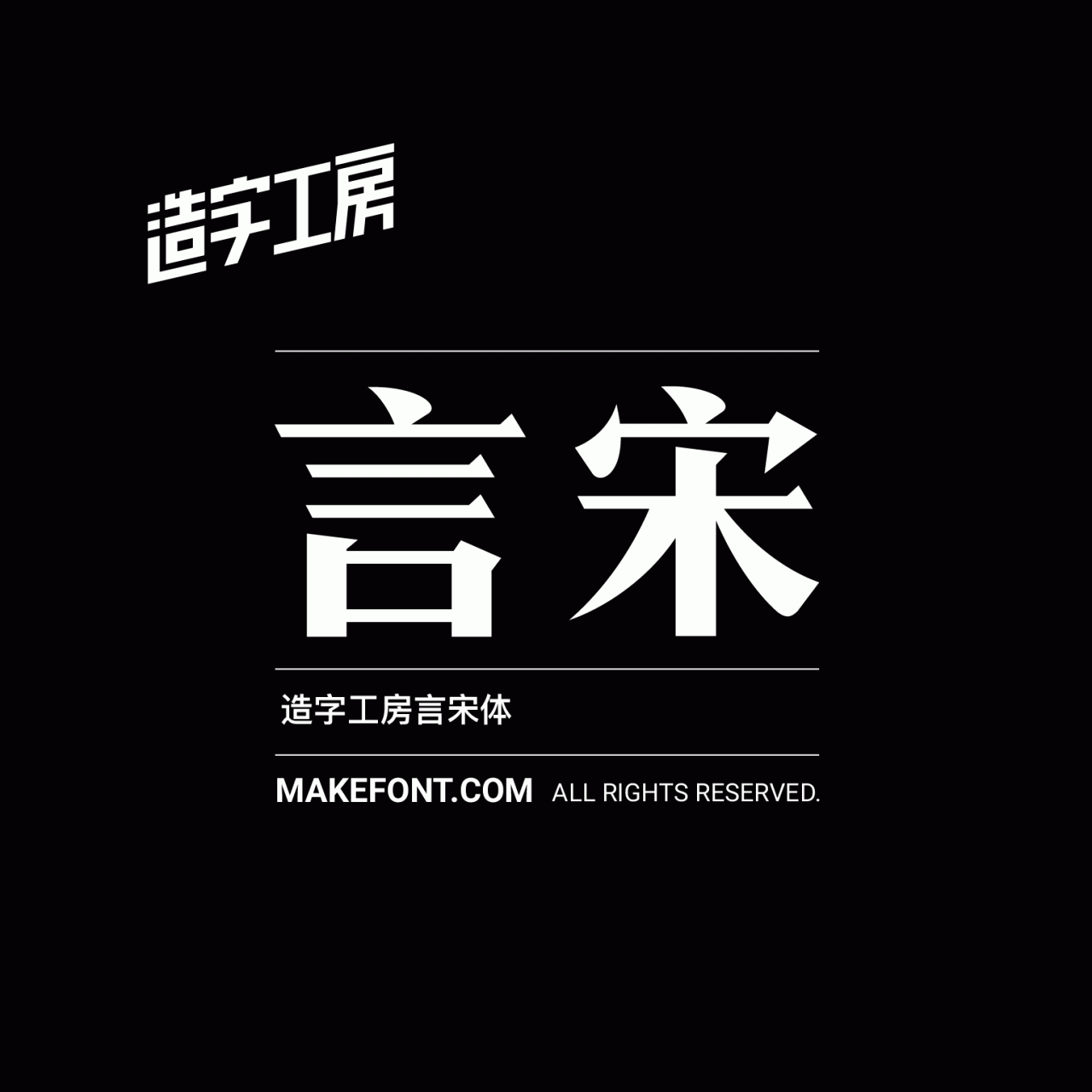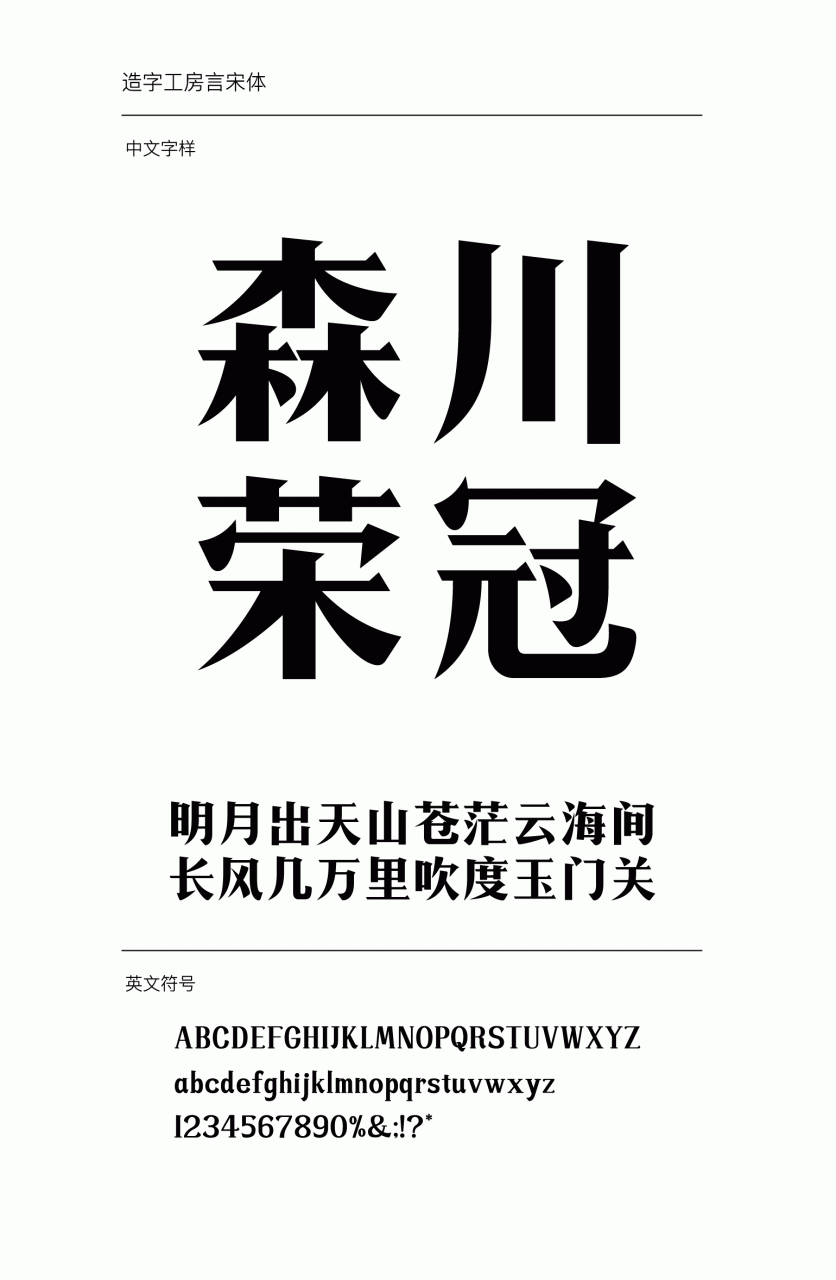
造字工房言宋常规体
造字工房言宋常规体设计说明
造字工房言宋体字体字形风格典雅,字身紧凑严谨,笔画舒展,横画的尖突与勾、点、提的圆润处理相呼应,刚柔并济、工整而不失精巧,最大程度的展现笔画的柔和秀美,有极强的视觉表现力,此款字体适用于报刊杂志及书籍、画报的主副标题和个性品牌设计推广等环境。 本字体为简体字库,采用OpenType/CID格式,Adobe-GB1-5编码。基于中华人民共和国GB2312-80字符集标准,另按需添加101个汉字。共收容字数6864CJK汉字,ASCII常用字符100个。